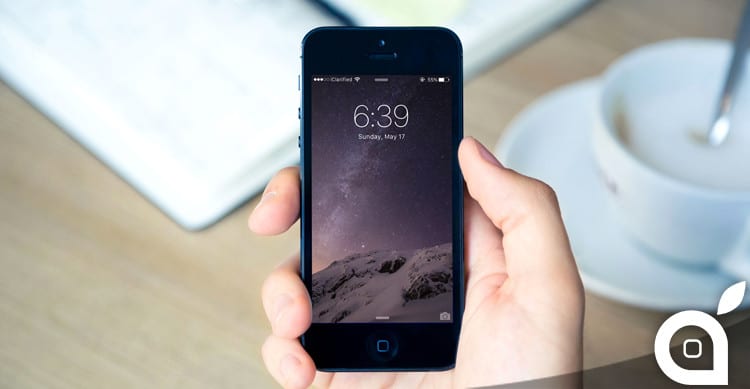
Ecco come avere il font dell’Apple Watch su iPhone | Cydia
Tra le previsioni delle novità di iOS 9 si è parlato di un nuovo font, attualmente utilizzato su Apple Watch. Il risultato in Lockscreen e all’interno del sistema operativo non è affatto male e qualcuno ha pensato bene di renderlo già disponibile tramite Cydia per tutti gli utenti che hanno il Jailbreak.
Successivamente, scaricate il font chiamato “San Francisco” ed applicatelo con Bytafont.